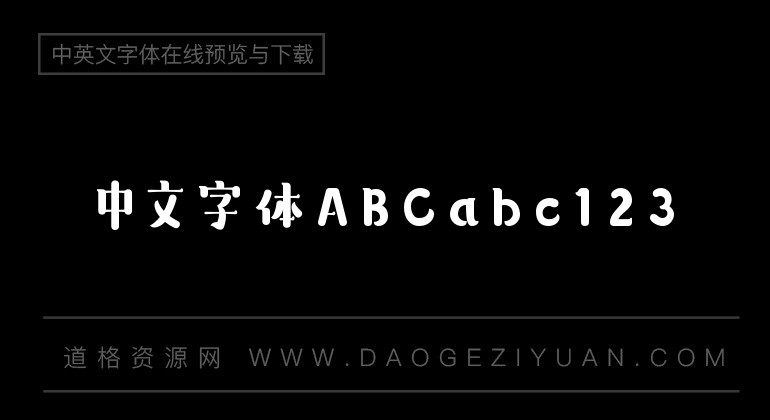
二字元山中辛巴体字体是一种比较独特的字体,它采用了非常醒目的设计风格。它的字形中融合了许多不同的元素,包括草书、隶书和楷书等。整体来说,这种字体比较适合用于各种印刷品、海报和设计项目中,因为它可以提供独特的视觉效果,并能够吸引读者的眼球。此外,它的设计风格也比较现代,符合当今设计的审美标准。文件名:ErZiYuanShanZhongXinBaTi-Shan(ACGN-SimbaGB-Flash)-2.ttf
二字元山中辛巴体是一款非常不错的手写艺术字体,具有很好的视觉感,适合于文化类的宣传设计、商业类品牌的广告和产品包装设计以及个性化文字排版等较多场景。